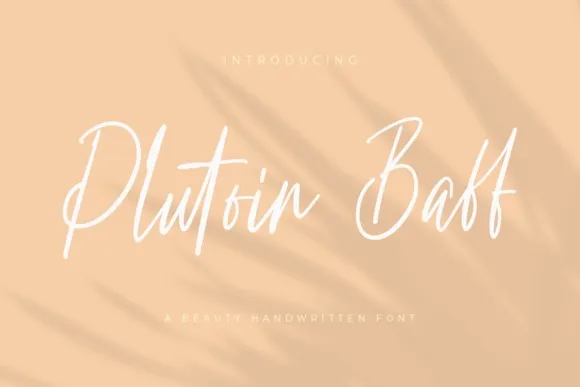
A fonte ‘Plutoin Baff’ é uma criação cuidadosamente pensada pelo Designer TempCraft no estilo de assinatura à mão escrita. Com letras afiadas e belas, ela resulta em fonts modernas, trendy e elegantes que se destacam com facilidade em diferentes ambientes de design. Perfeita para uso nos blogs, mídias sociais, marcas, embalagens de produtos, convites de casamento, headshots, sinalização, etiquetas, capas de livros, outdoors, cartazes e citações, a ‘Plutoin Baff’ oferece uma versatilidade que vai além do texto simples. Seja ela a cara de um site dinâmico ou o coração de sua próxima campanha visual, esta font cativará seu público-alvo com um toque sofisticado e criativo. Com o ‘Plutoin Baff’, você pode transformar suas ideias em realidade, oferecendo ao mesmo tempo uma experiência única para os seus usuários ou clientes.